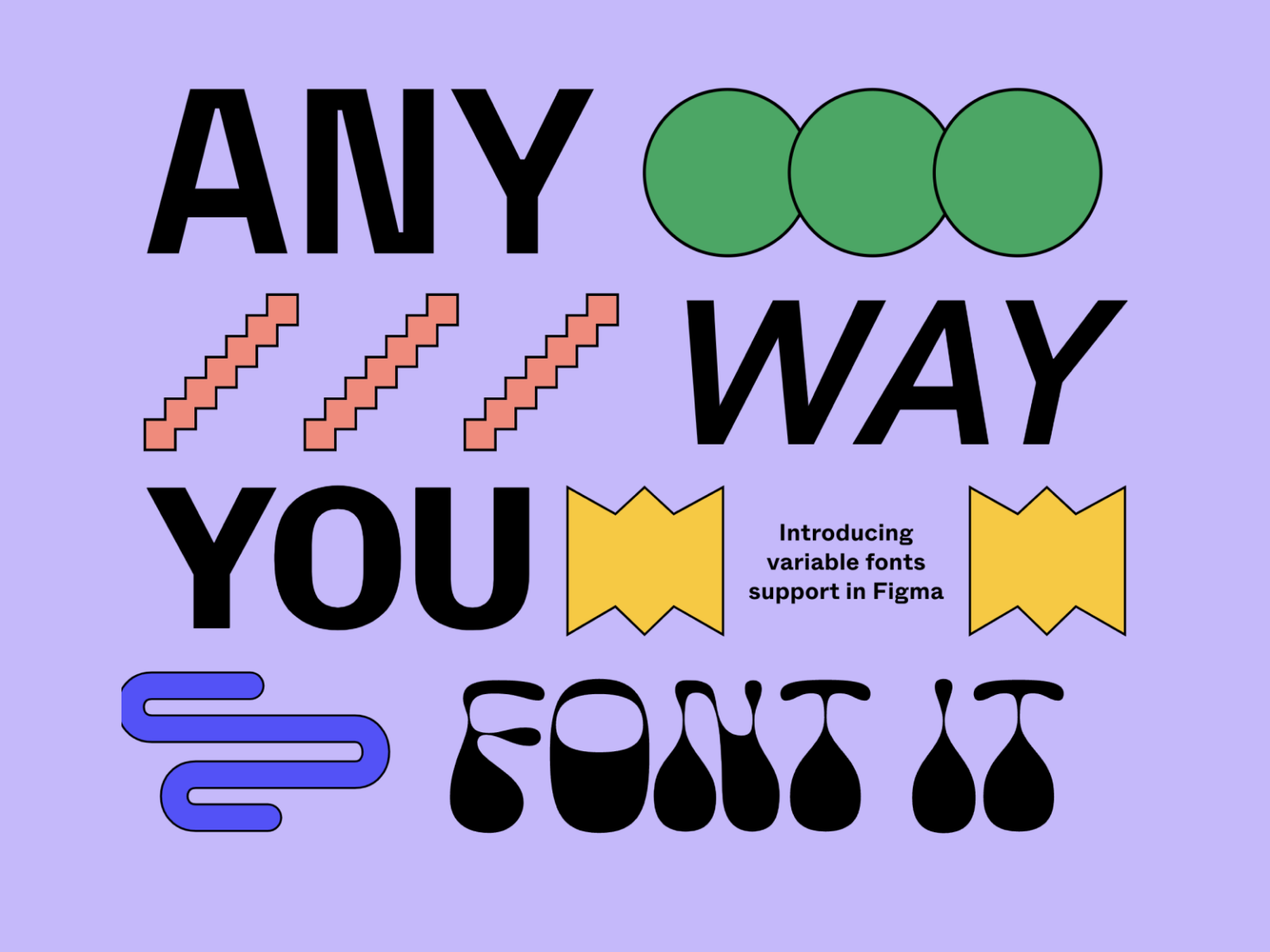
피그마 가변 글꼴: 내 맘대로 글꼴 주무르기
피그마가 새로운 가변 글꼴 (Variable fonts)을 다뤄볼 수 있는 웹사이트를 공개했습니다.
가변 글꼴은 하나의파 일로 너비, 두께, 기울기 등을 자유자재로 변경할 수 있는 차세대 글꼴 포맷입니다. 어도비, 애플, 구글, 마이크로소프트가 협업해 개발했으며 2016년 발표된 기술입니다.
👁️ 디자이너의 눈
마우스를 올리면 반응하는 첫 상호작용이 매력적입니다. 귀여운 일러스트레이션 위에 마우스 커서를 올려 좌우로 움직이면 반응합니다. 글꼴의 속성에 영향을 미치는 다양한 축을 직관적으로 표현했습니다.
가변 글꼴을 바로 이해할 수 있게 직관적으로 설명합니다. 글꼴 파일 1개로 다양한 서체의 속성을 지정해 사용할 수 있습니다. Thin, Regular, Black와 같은 굵기나 Italic, Condensed 등의 스타일을 위해 별도 글꼴 파일을 사용할 필요가 없습니다. 마치 여러 개의 png 이미지를 쓰는 대신 자유자재로 쓸 수 있는 svg 파일을 사용하는 것 같습니다.
섬세한 디테일은 곧 사용성과 심미성에 연결됩니다. 글의 크기와 량에 따라 적절한 글꼴을 사용할 수 있습니다. 글자의 크기가 작아지면 글꼴이 더 두꺼워보이는데 크기에 따라 적절한 굵기를 지정할 수 있습니다. 버튼을 디자인할 때 글꼴의 속성을 바꾸면 레이어의 크기가 바뀔 수도 있는데 크기는 고정되면서 굵기만 바꿀 수 있습니다. 폭을 좁혀 좁은 공간에 더 많은 글자를 넣을 수도 있습니다. 시간축을 설정할 수 있어 애니메이션도 넣을 수 있습니다.
📕 에디터 노트
서비스가 새롭게 제공하는 기능을 소개하는 방식이 멋집니다. 피그마다운 그래픽으로 알기 쉽게 개념을 설명하고 직접 사용해보게 만드는 것이 직관적입니다. 피그마 툴을 바로 써보게 할 수도 있지만 살펴볼 기능에만 집중하는 것도 쉽지 않습니다. 하고 싶은 말만 압축해서 매력적인 웹사이트로 공유한 것이 매력적입니다.